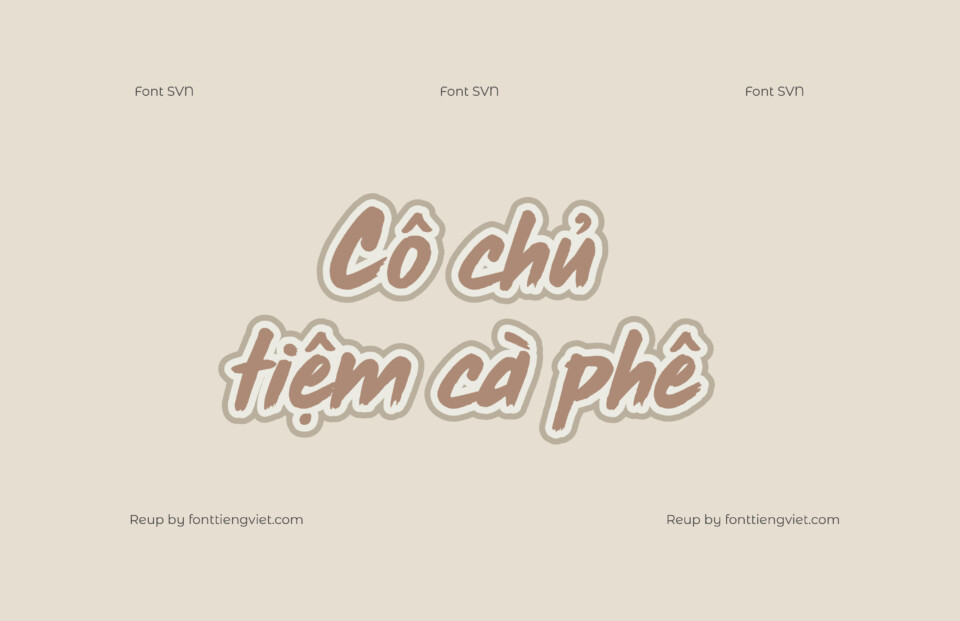
Font Việt hóa SVN Rush Hour
Trong thế giới đồ họa hiện đại, việc lựa chọn một bộ Font Chữ phù hợp là yếu tố tiên quyết để tạo nên dấu ấn riêng biệt cho mọi tác phẩm. Đối với những nhà thiết kế đang tìm kiếm sự phá cách và năng động, Font Việt hóa SVN Rush Hour chính là lựa chọn hoàn hảo nhất. Đây là một bộ phông chữ thuộc phong cách Brush mang hơi hướng đường phố, thể hiện sự mạnh mẽ và tốc độ đúng như tên gọi của nó. Khi sử dụng phiên bản Việt hóa từ đội ngũ SVN, bạn sẽ hoàn toàn yên tâm về khả năng gõ tiếng Việt có dấu chuẩn xác, không lo lỗi hiển thị trong quá trình làm việc trên các phần mềm đồ họa chuyên dụng.
Đặc điểm nổi bật của Font Việt hóa SVN Rush Hour
Phong cách thiết kế thủ công ấn tượng
Font Việt hóa SVN Rush Hour sở hữu những đường nét được vẽ tay tỉ mỉ, tạo ra các vệt xước tự nhiên giống như được vẽ bằng cọ sơn hoặc bút dạ lớn. Chính sự thô ráp này mang lại cảm giác phóng khoáng, rất phù hợp cho các dự án thiết kế banner quảng cáo, áo thun hay bìa album ca nhạc. Đặc biệt, bộ phông này hỗ trợ rất tốt cho các tiêu đề lớn cần sự thu hút thị giác mạnh mẽ ngay từ cái nhìn đầu tiên.
Tính ứng dụng cao trong học tập và đời sống
Không chỉ giới hạn trong giới chuyên nghiệp, học sinh và giáo viên cũng có thể sử dụng bộ phông này để làm sinh động các bài thuyết trình hoặc thiết kế báo tường. Sự độc đáo của các ký tự giúp nội dung trở nên gần gũi và thú vị hơn đối với người xem.